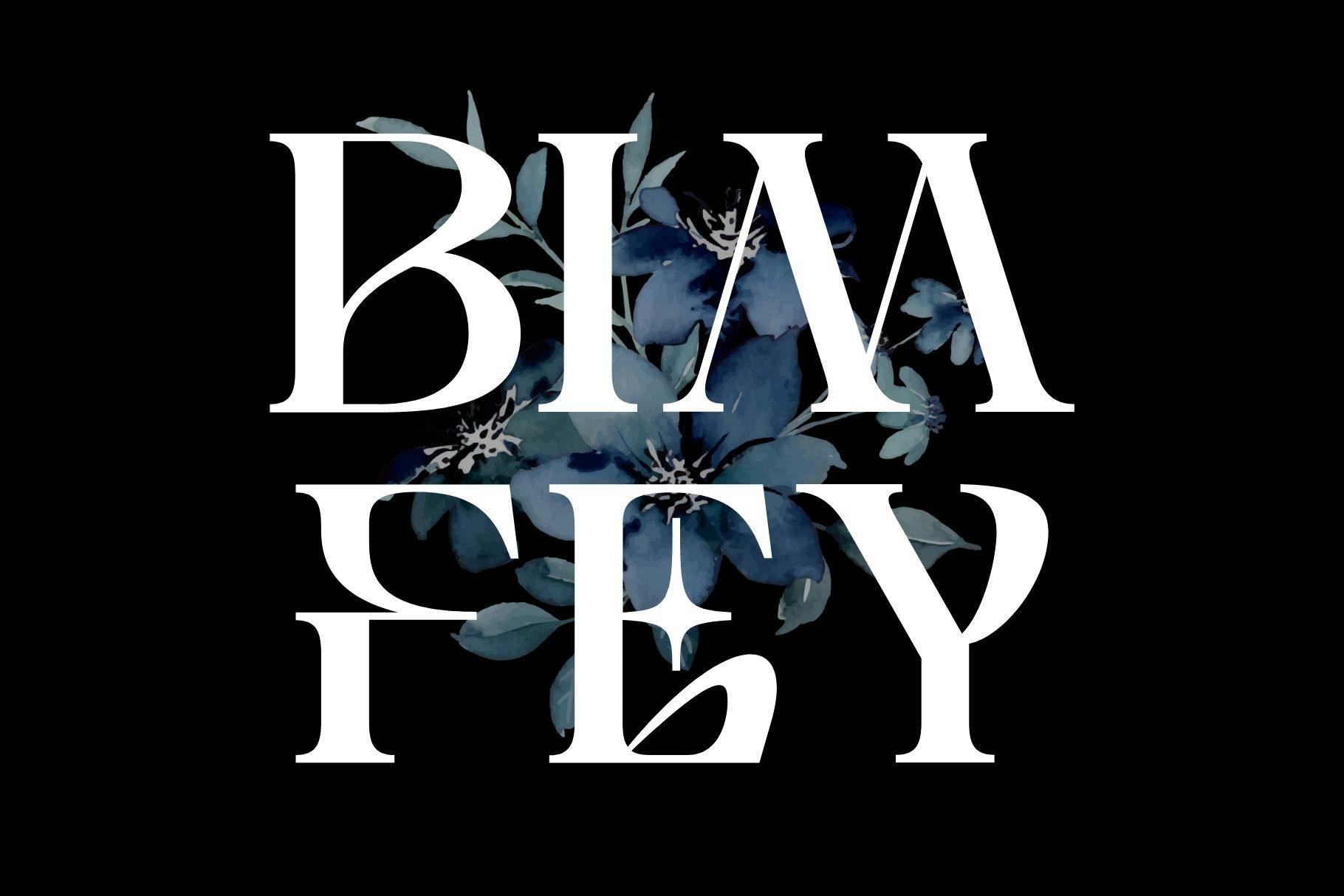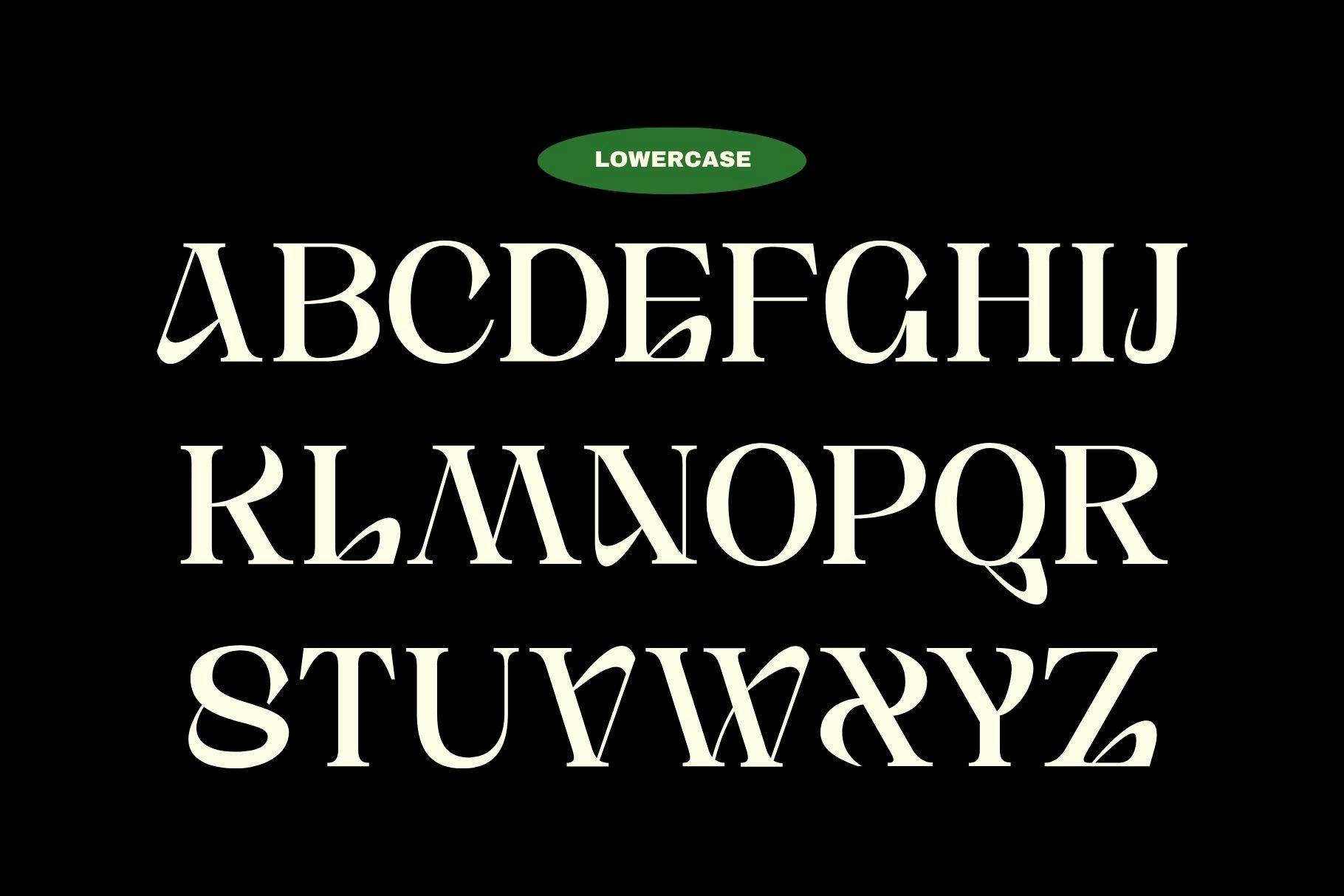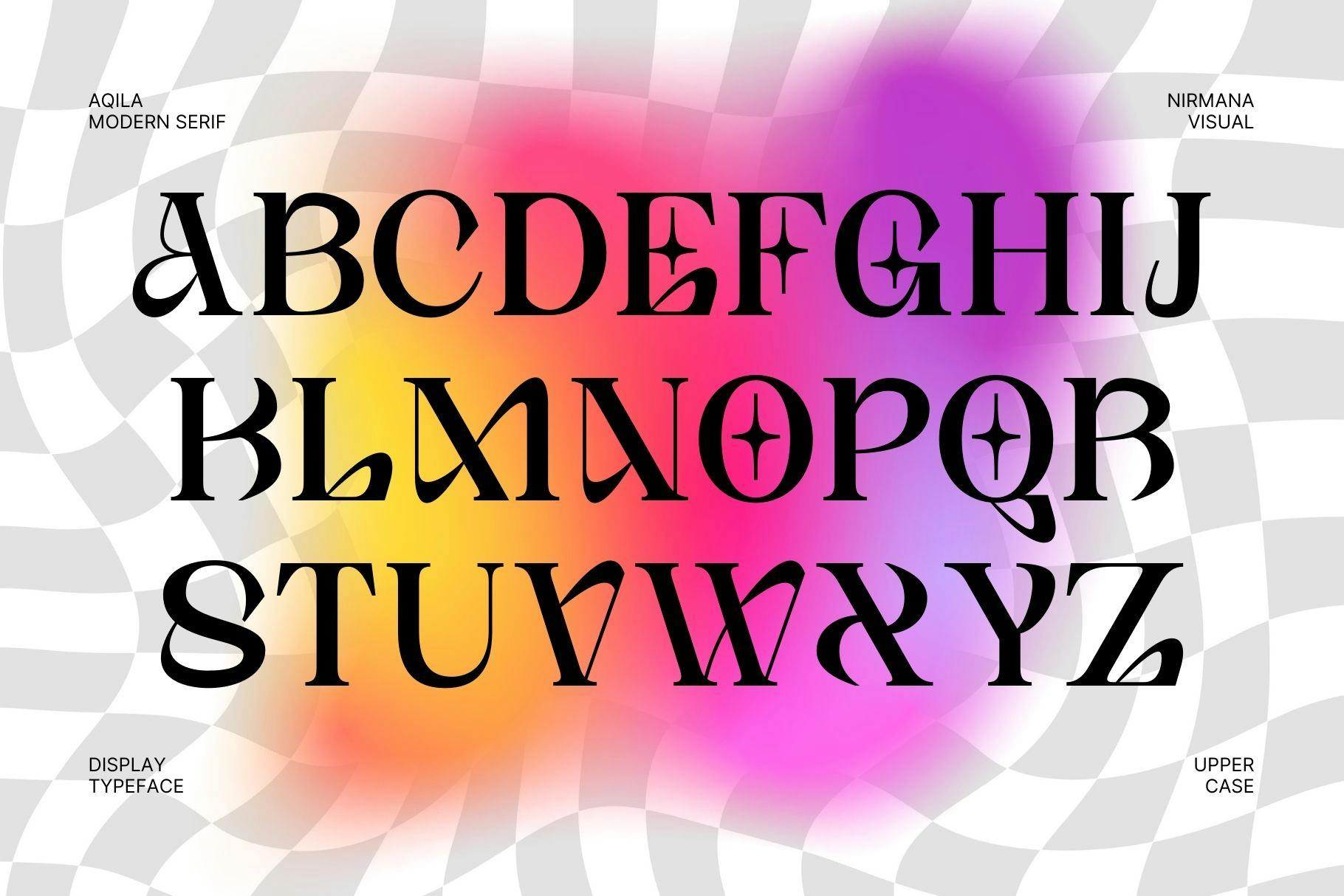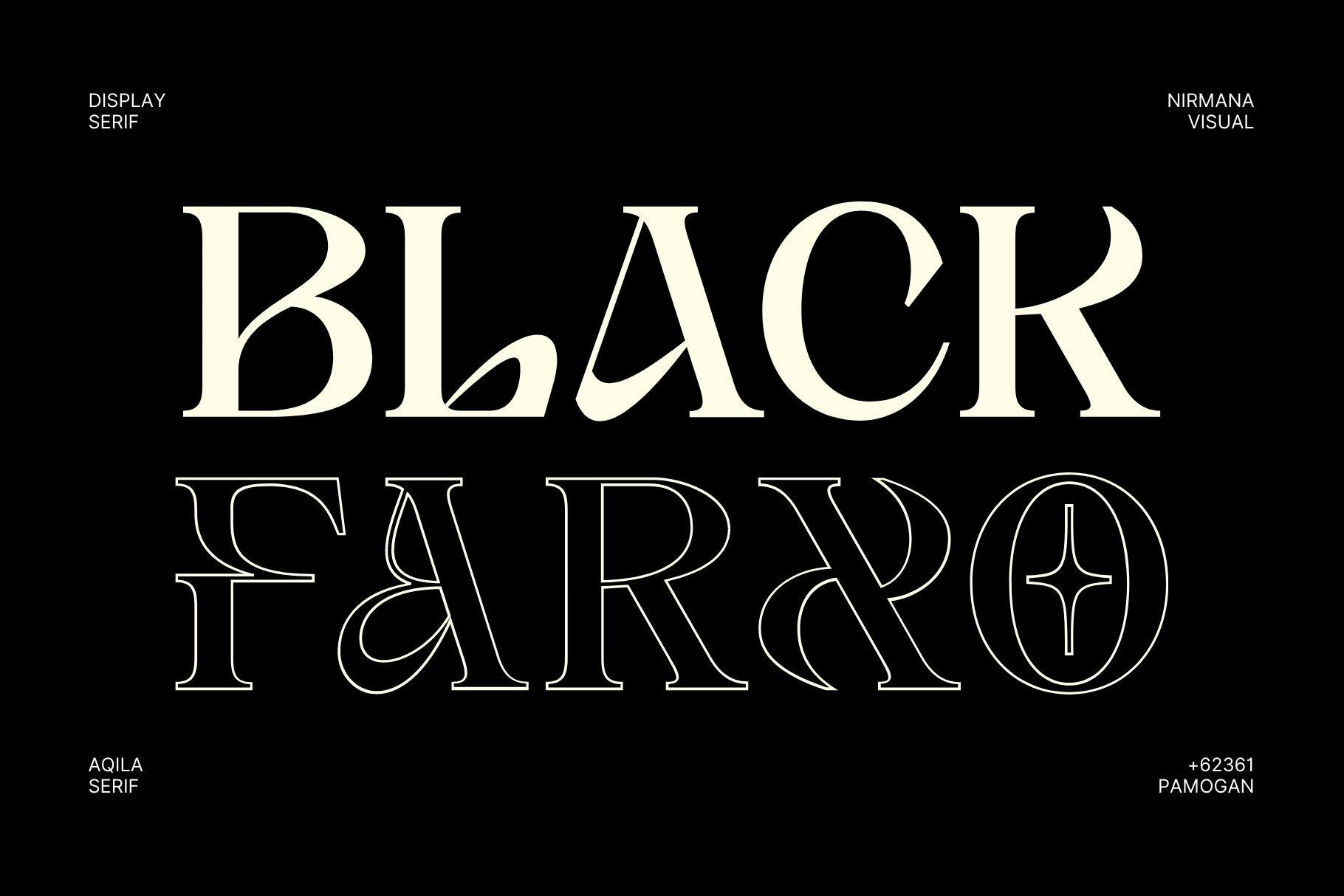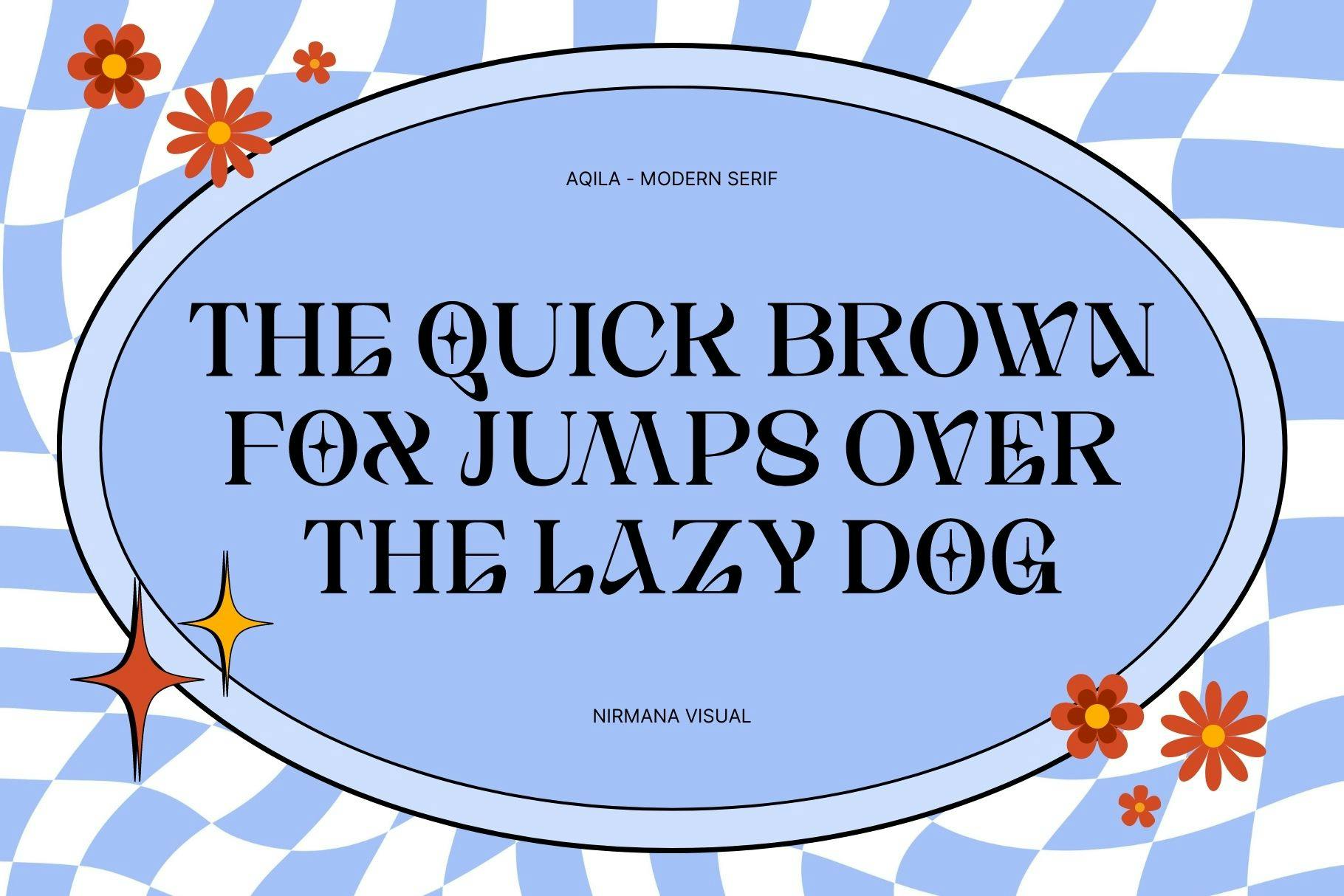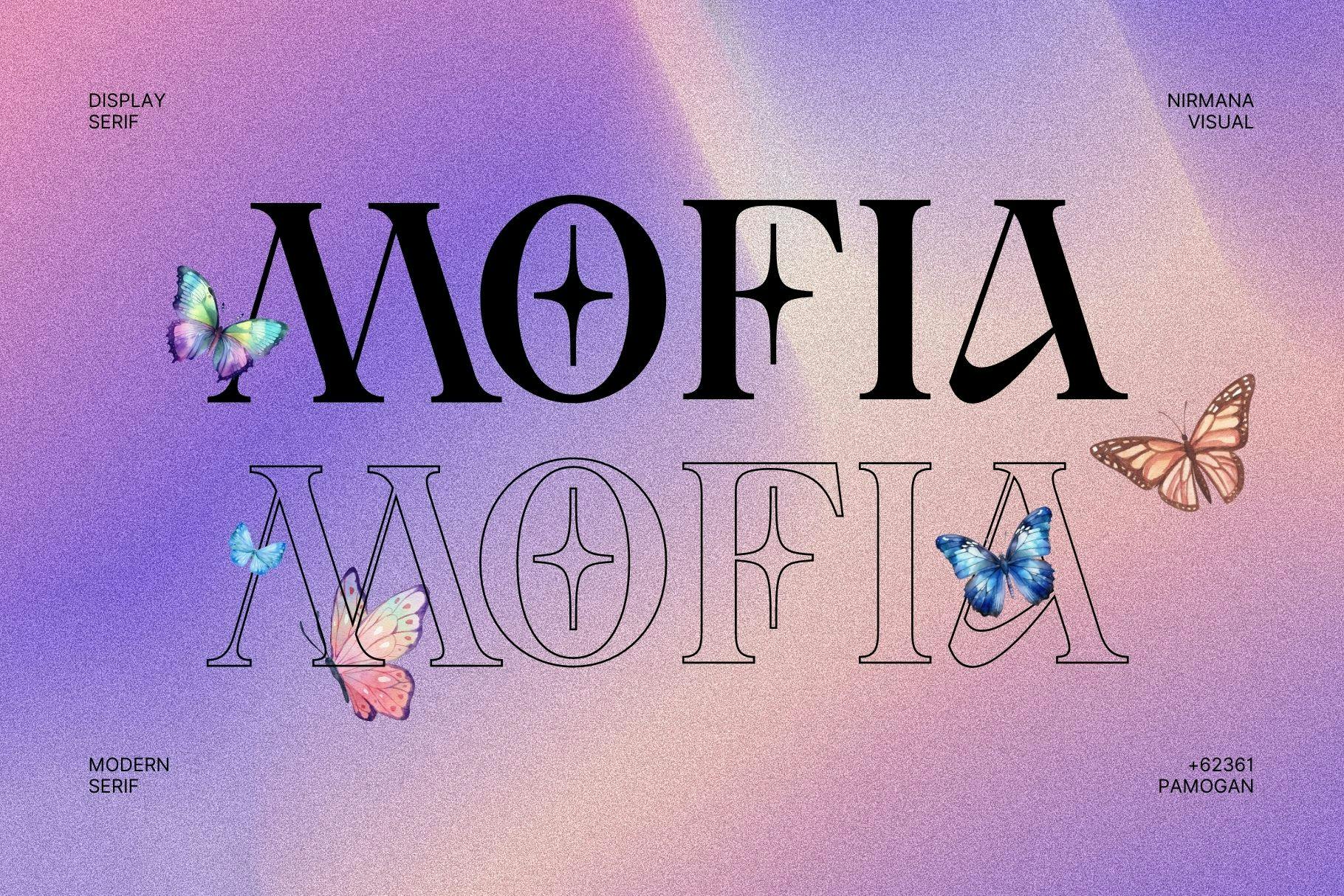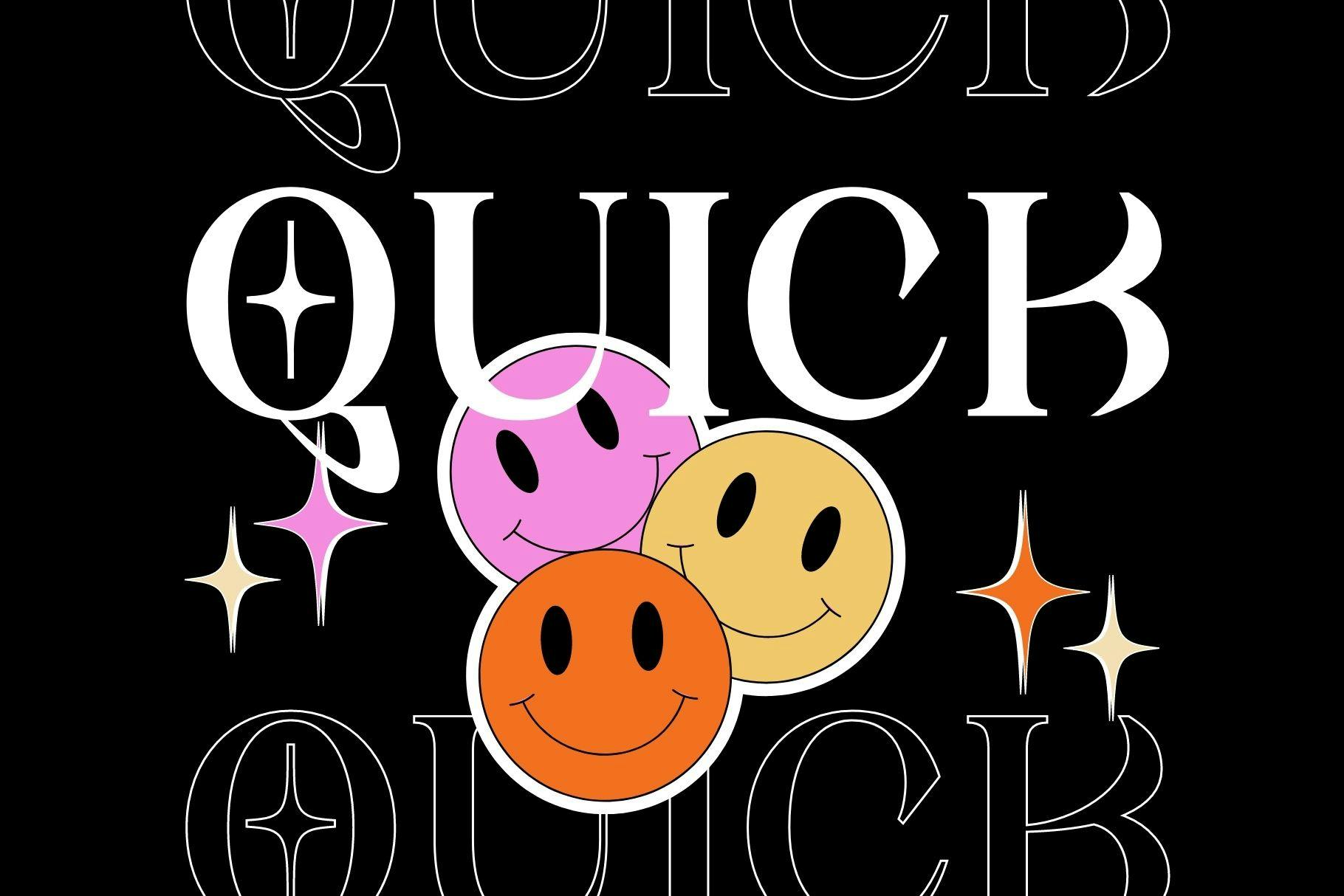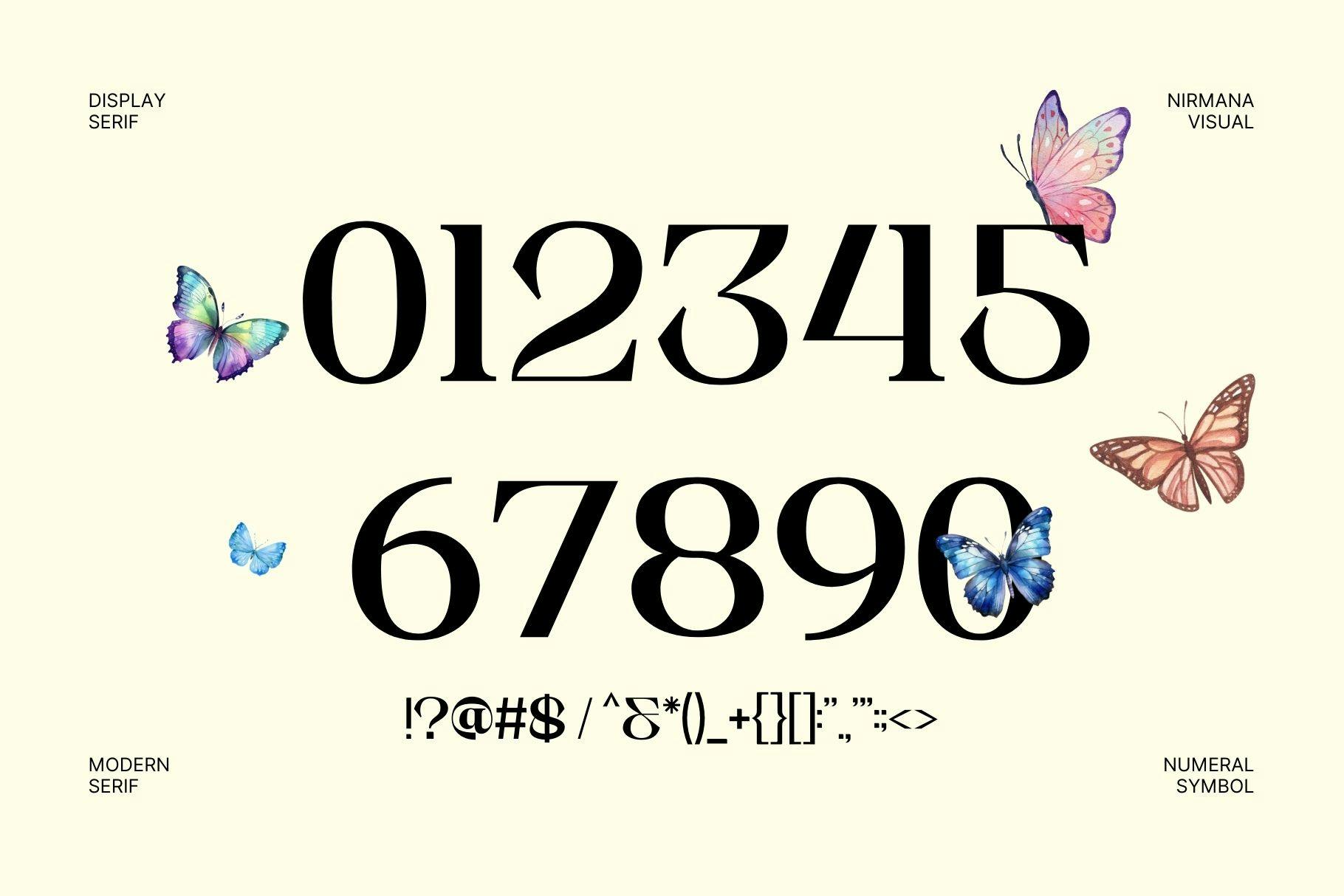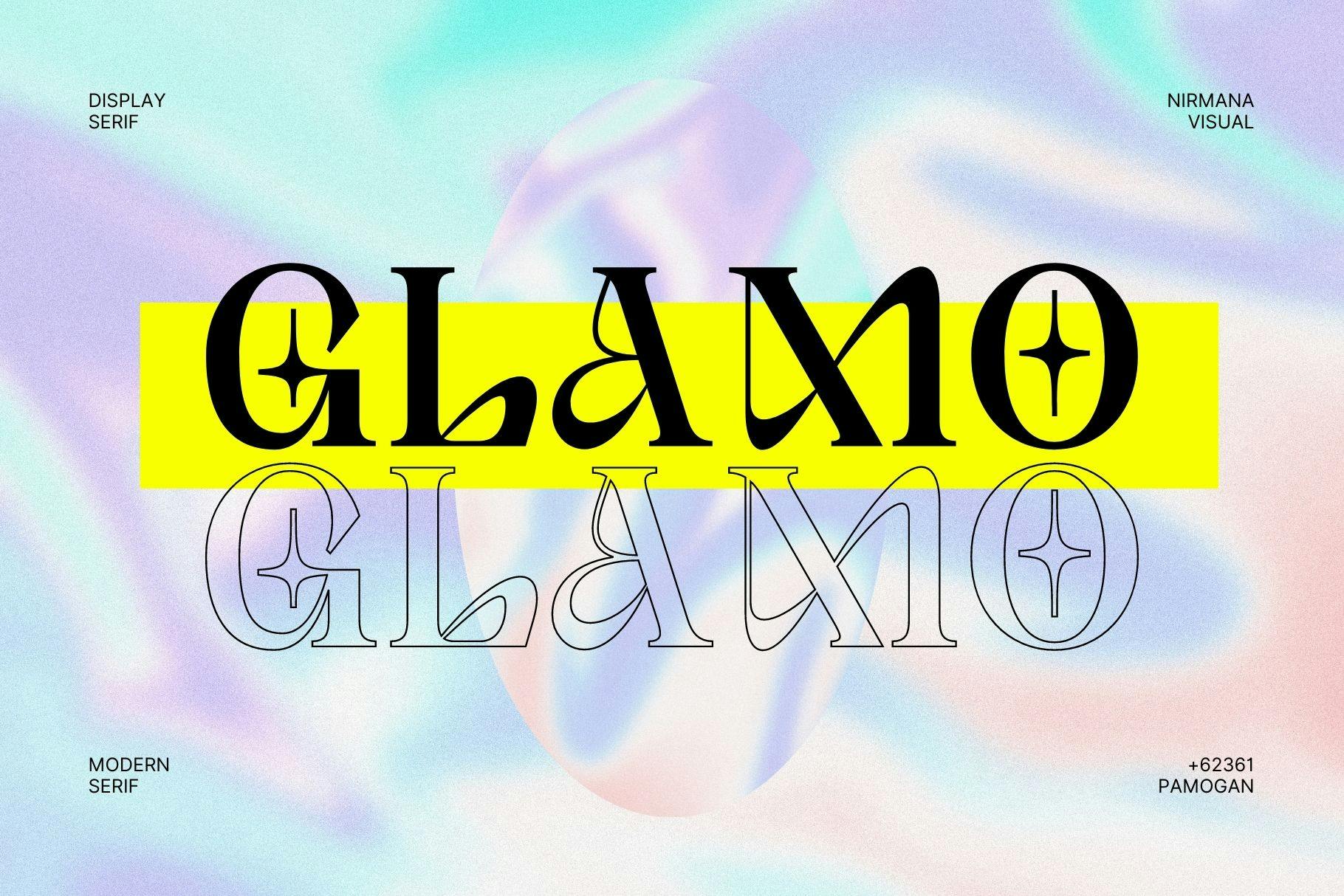
دانلود فونت لوکس آکیلا با طراحی زیبا
Aqila Elegant Luxury Font
فونت آکیلا با طراحی لوکس و زیبا، گزینه‌ای عالی برای پروژه‌های شماست.
آکیلا - فونت لوکس
فونت آکیلا هارمونی زیبای تایپوگرافی را برای تنوعی از پروژه‌های طراحی فراهم می‌کند، از جمله لوگو و برندینگ، پست‌های رسانه‌های اجتماعی، تبلیغات و طراحی محصولات.